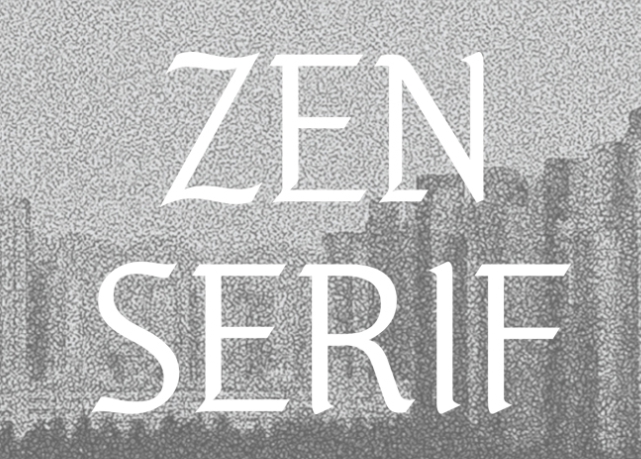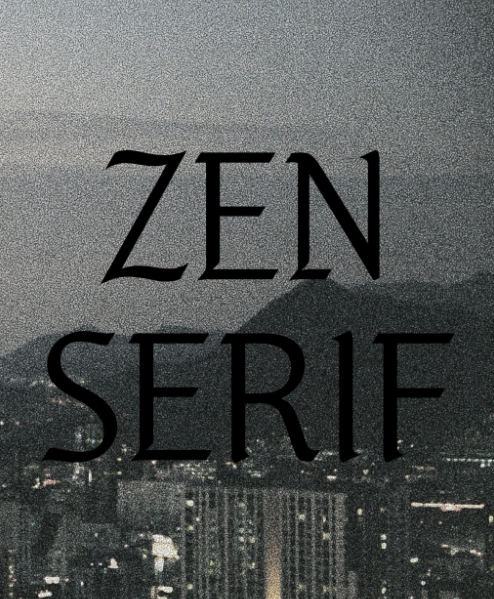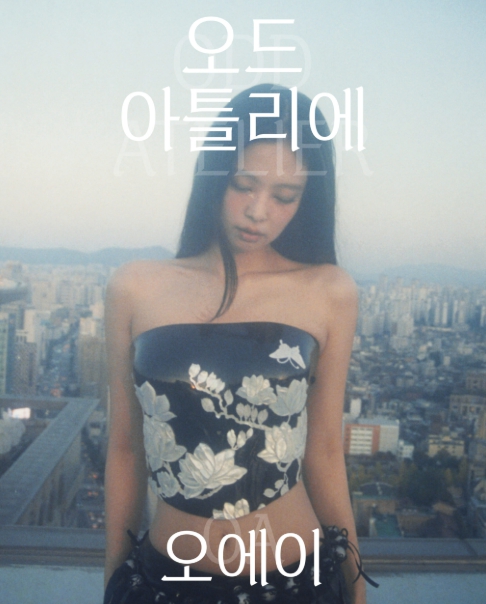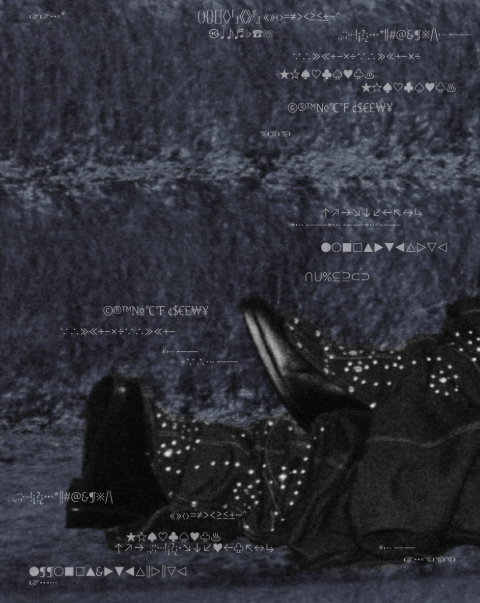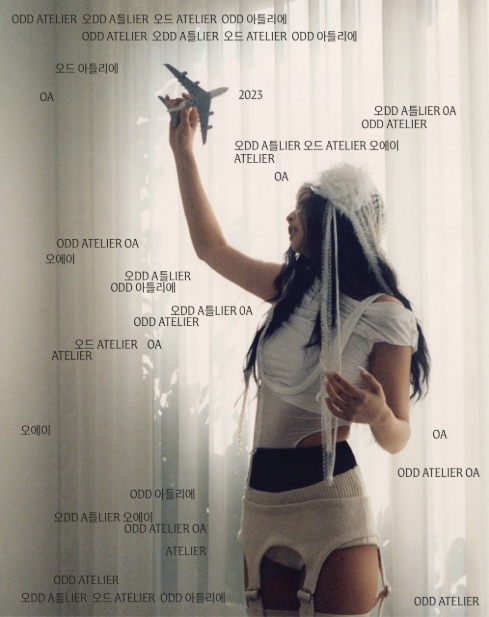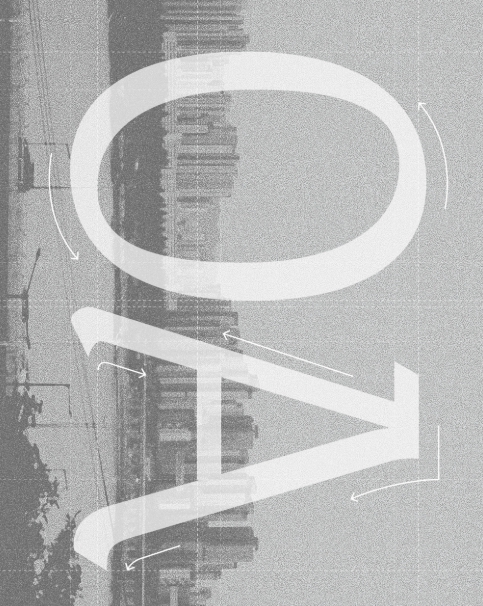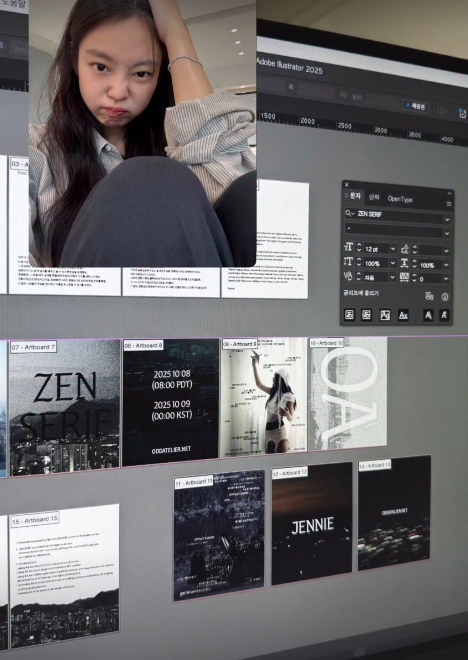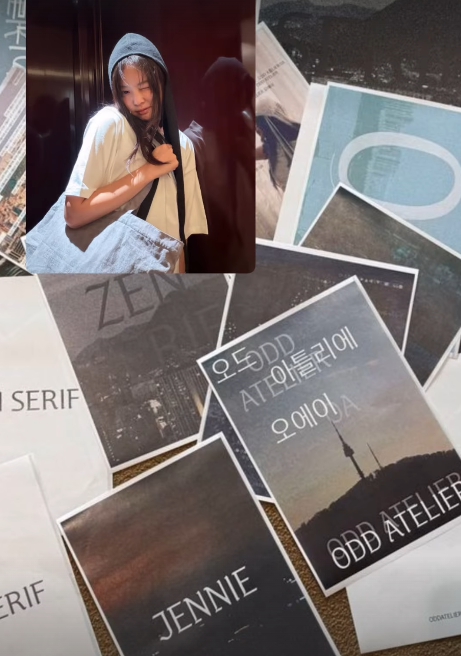
요즘 블로그, 인스타그램, 유튜브 썸네일 등에서 감성적인 디자인을 완성하는 폰트로
_제니 폰트(ZEN SERIF)_가 큰 인기를 얻고 있습니다 ✨
고급스럽고 세련된 세리프 디자인 덕분에
디자이너, 크리에이터, 셀러, 블로거까지 폭넓게 사용하고 있죠.
🖋️ 제니 폰트(ZEN SERIF)란?
‘ZEN SERIF(젠 세리프)’는
제니(JENNIE)와 OA 아틀리에(Odd Atelier)가 함께 제작한 정식 폰트입니다.
- 한글·영문 완벽 지원
- 고급스러운 세리프(Serif) 스타일
- 포스터, 썸네일, 블로그, PPT 등 어디서나 활용 가능
✨ 제니 특유의 감성적인 분위기를 담은 프리미엄 무료 폰트입니다.
고급감 + 감성 디자인 연출에 탁월합니다.
감성을 완성하는 폰트, 제니 폰트(ZEN SERIF) 🎀
무료지만 디자인 퀄리티는 프리미엄급입니다.